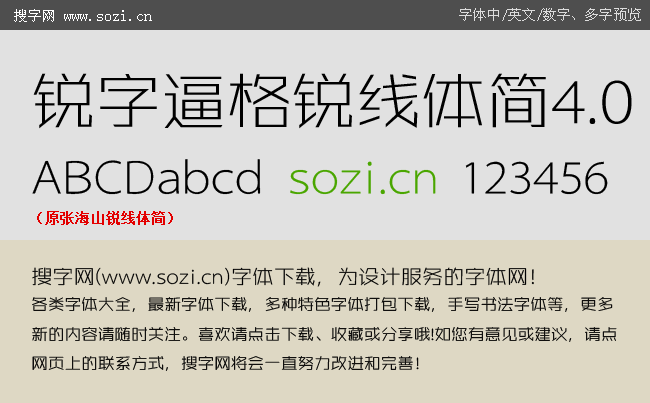
銳字逼格銳線體簡(jiǎn)4.0
搜字網(wǎng)提供一款銳字逼格銳線體簡(jiǎn)4.0中文字體下載,銳字逼格銳線體是一款應(yīng)用于設(shè)計(jì)方面的中文簡(jiǎn)體漢字,該字體端正大方,擁有卡通風(fēng)格,整體效果非常出眾,并且字庫(kù)完整,可以應(yīng)用于廣告設(shè)計(jì)、名片設(shè)計(jì)、包裝印刷、產(chǎn)品設(shè)計(jì)等應(yīng)用。